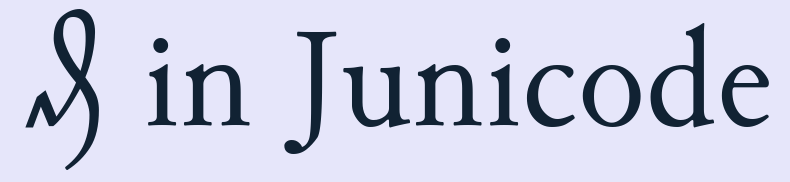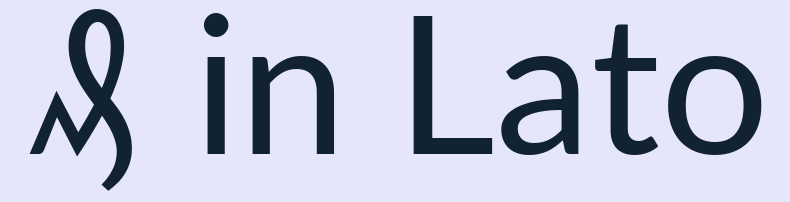
Pfennigzeichen fehlt in Sabon Next – was tun?
Wir sind nun fast fertig mit dem Setzen eines Textes bestehend aus Abschriften alter Briefe und Tagebucheinträge. Als Schrift ist die Sabon Next gewählt und bereits für teuer Geld lizensiert. Nun merke ich, dass das Pfennigzeichen fehlt: ₰ (Unicode U+20B0)
Aus welcher Schrift können wir Ersatz nehmen, der typografisch passt?
Auf der Lynotype-Seite erscheint das Zeichen interessanterweise bei der Online-Variante, allerdings nicht einheitlich in Chrome und Firefox (Windows 7). Möglicherweise haben die Browser hier automatisch für Ersatz gesorgt:
• Chrome:
• Firefox:
Zunächst habe ich jetzt einfach mal Times New Roman für das Pfennigzeichen genommen:
Ich habe mal in meinem bescheidenen¹ Katalog freier Schriften gesucht. Mit
findest du alle dort vorhandenen Schriften, die ein ₰ enthalten.
Ein paar Beispiele, die für dich interessant sein könnten:
1. Nur 116 Familien, aber immerhin praktisch alle, die hier im Wiki verzeichnet sind, also wohl die meisten der „wichtigsten“.
Wenn das Buch nicht in Fraktur gesetzt wird, könnte vielleicht auch das kleine »d« aus der Kurrentschrift, das das Pfennigzeichen ist, weggelassen werden. Es ist seit Jahrzehnten außer Gebrauch. Ich selbst denke, wenn ich es sehe, nicht an Pfennig, sondern an Deleatur (statt Denarius), weil es dem Korrekturzeichen so ähnelt. Aber im Kontext liest es sich sicherlich eindeutig. Man könnte für die Verständlichkeit aber durchaus »Pf.« setzen.
Ich habe mal in meinem bescheidenen¹ Katalog freier Schriften gesucht. Mit
findest du alle dort vorhandenen Schriften, die ein ₰ enthalten.
Man könnte für die Verständlichkeit aber durchaus »Pf.« setzen.
Danke für den Vorschlag. Nur wir möchten die Typografie so wie im handschriftlichen Original belassen.
Schade, dass keine Garamond dabei ist.
Gibt es überhaupt ein garamondtypisches ₰? :-? Mit anderen Worten: würde der typische Leser es einem ₰ (aus einer „klassischen“ Serifenschrift) überhaupt ansehen, woher es kommt?
Ansonsten wäre da noch die Andron. Ist dein Projekt nicht kommerziell, käme vielleicht die kostenlose Andron Scriptor Web in Frage, ansonsten eine der kommerziellen Versionen.
Ach ja, ich habe ja auch Mark und Pfennig in meinem Setzkasten herum schwirren:
Jetzt mal eine Frage an die „Bleiklötzchen-Fraktion“: Waren diese Zeichen überhaupt im Lieferumfang einer Schrift enthalten, oder war das so ein Spezialsatz mit derartigen Sonderzeichen? Und wenn ja, was war da eigentlich normalerweise noch enthalten?
Gibt es überhaupt ein garamondtypisches ₰? :-? Mit anderen Worten: würde der typische Leser es einem ₰ (aus einer „klassischen“ Serifenschrift) überhaupt ansehen, woher es kommt?
Auf keinen Fall. Deshalb wies ich auf die Fraktur hin. Zur Antiqua ist das Zeichen vollkommen fremd (selbst wenn es eine eindeutige Garamond gäbe). Wenn man es verwendet, muß man deshalb nicht auf den Federduktuktus achten, der kann auch gegensätzlich zur Druckschrift sein. Wohl achten sollte man aber auf die Helligkeit und die Maßverhältnisse, so daß das Zeichen nicht als Blickfang aus der Seite sticht. Eine Textstörung ist es immer. In der Liste oben sind die der Charis und Gentium viel zu klein, das der Symbola zu fett, das der Junicode zu groß. Also obwohl sie vorgeblich zur Schrift gemacht sind, sind sie für den Einsatz im Text dieser Schrift untauglich und sollten besser ausgetauscht werden. So wie es auch zu viele Schriften mit einem unbrauchbaren @ gibt, obwohl man das ungleich häufiger benötigt als ein Pfennigzeichen.
Jetzt mal eine Frage an die „Bleiklötzchen-Fraktion“: Waren diese Zeichen überhaupt im Lieferumfang einer Schrift enthalten, oder war das so ein Spezialsatz mit derartigen Sonderzeichen? Und wenn ja, was war da eigentlich normalerweise noch enthalten?
Zeichen für Währungen gehörten begrenzt auf den Gießzettel. Manchmal das Dollarzeichen, manchmal Pfund; Mark und Pfennig noch seltener. Einzelne Sonderzeichen konnte man von der Schriftgießerei in beliebigen Mengen kaufen. In den Sonderzeichensammlungen steckt alles, was nicht im Setzkasten steckt, also alles für naturwissenschaftliche Fomeln, Prozentrechnung, Kaufmännisches. Diese Sammlungen sehen in jeder Setzerei anders aus. Auf Schriftcharaktere wird dabei natürlich keine Rücksicht genommen. Daß ich zwei Varianten @ habe, liegt nur daran, daß es noch mehr als eine Schriftgießerei gab, als ich anfing.